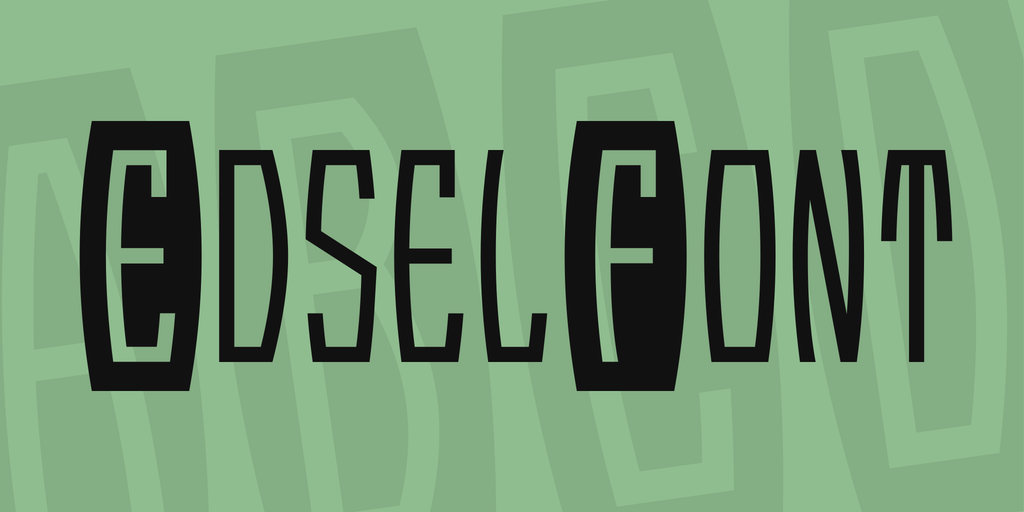
A EdselFont Font é uma elegante escolha para designers que buscam uma tipografia alegre e envolvente. Inspirada no estilo display, ela oferece um toque moderno com traços finos e detalhes sutis que vão perfeitamente com texturas de desenho animado ou fotografias de alta resolução. Desenvolvida pelo designer Hamilton, essa fonte é ideal para aplicativos digitais e sites de jogos. Seu design contínuo e arredondado cria um visual atraente que destaca qualquer texto em uma página web. Além disso, sua facilidade de combinação com outras fontes garante que sua tipografia seja esteticamente harmoniosa. EdselFont é perfeito para criar designs que chamem atenção, tanto quanto manter um design minimalista. Seja para anúncios digitais, capas de aplicativos móveis ou logotipos de marcas digitais, esta fonte atinge simultaneamente esses dois objetivos de maneira convincente.